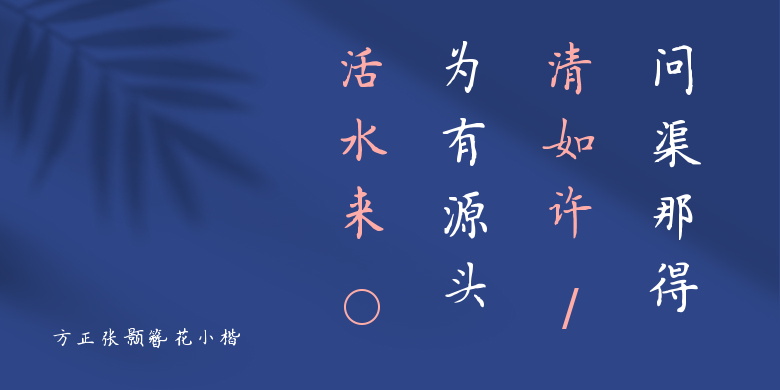
方正张颢簪花小楷
方正张颢簪花小楷,这款字体结构工整、笔画清晰,兼顾美观与易读性,适用于标题、正文、海报、包装、LOGO 等多种场景。字形优雅稳定,风格百搭耐看,适配日常排版与创意设计,让文字呈现更舒适、更具质感。方正张颢簪花小楷一笔一画,皆是细节,以均衡的比例、流畅的线条打造舒适视觉体验,字形端正大气,风格简约现代。无论是商业设计、品牌宣传还是日常排版,都能轻松驾驭,让文字更有格调与力量。方正张颢簪花小楷字体下载。